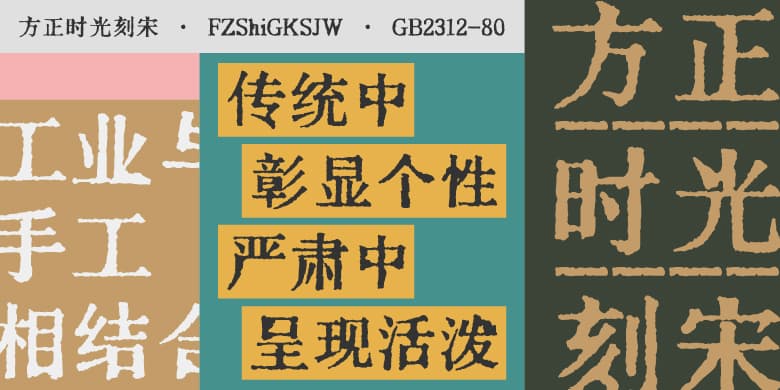
品牌:方正字库设计师:田玄丹,卫欢欢发行时间:2021字库编码:大陆简体(GB2312-80)分类:宋体字体属性:精品字
时光刻宋的独特洇染纹理来源于油墨过剩的印刷意外。这款字全部由人工仿画而成,却给人一种天然拓印的视觉效果。时光刻宋将工业与手工相结合,于传统中彰显个性,于严肃中呈现活泼,于怀旧中显现时尚。适用于电影海报、品牌名称、商号招牌、各类商业海报、媒体标题等。
品牌:方正字库设计师:田玄丹,卫欢欢发行时间:2021字库编码:大陆简体(GB2312-80)分类:宋体字体属性:精品字
时光刻宋的独特洇染纹理来源于油墨过剩的印刷意外。这款字全部由人工仿画而成,却给人一种天然拓印的视觉效果。时光刻宋将工业与手工相结合,于传统中彰显个性,于严肃中呈现活泼,于怀旧中显现时尚。适用于电影海报、品牌名称、商号招牌、各类商业海报、媒体标题等。